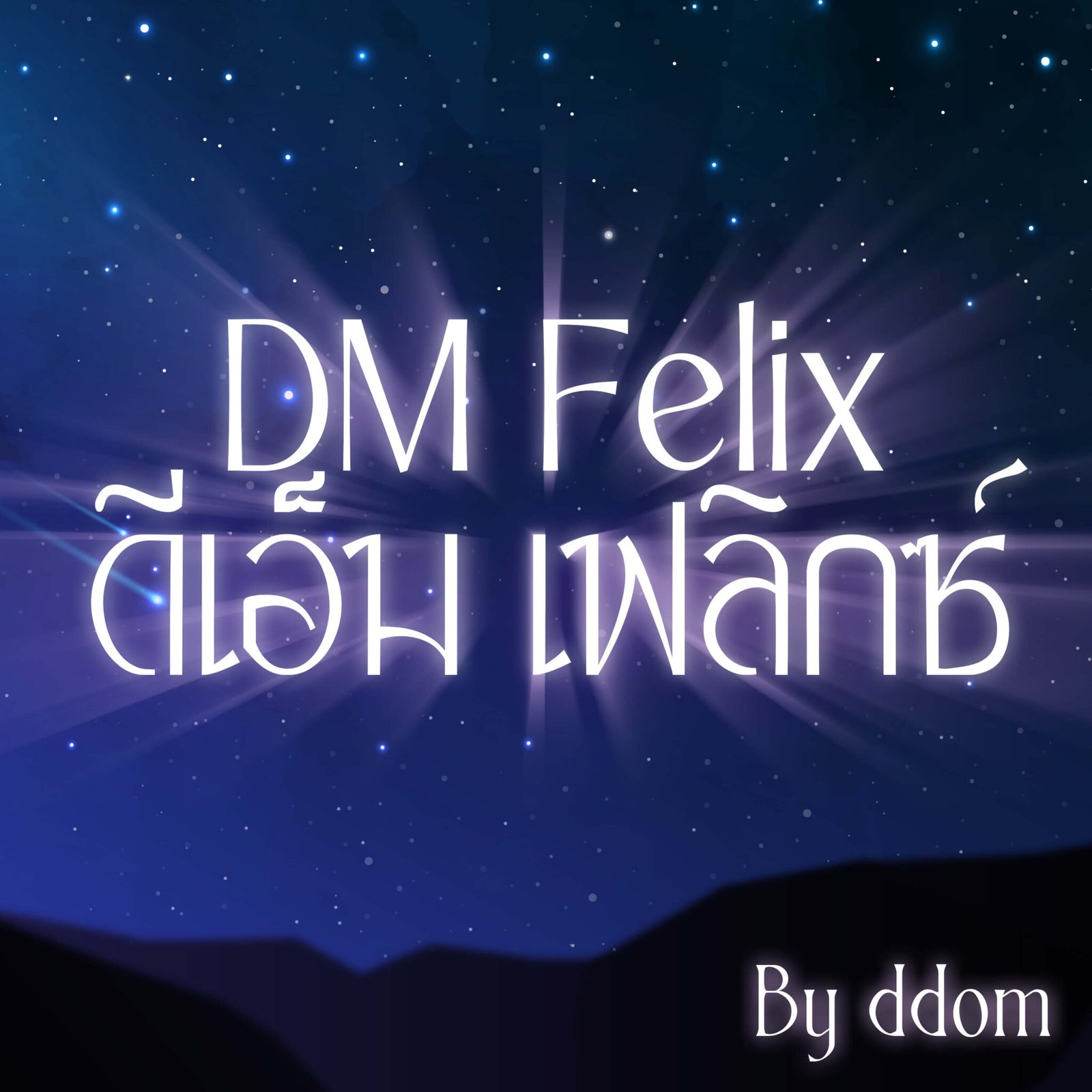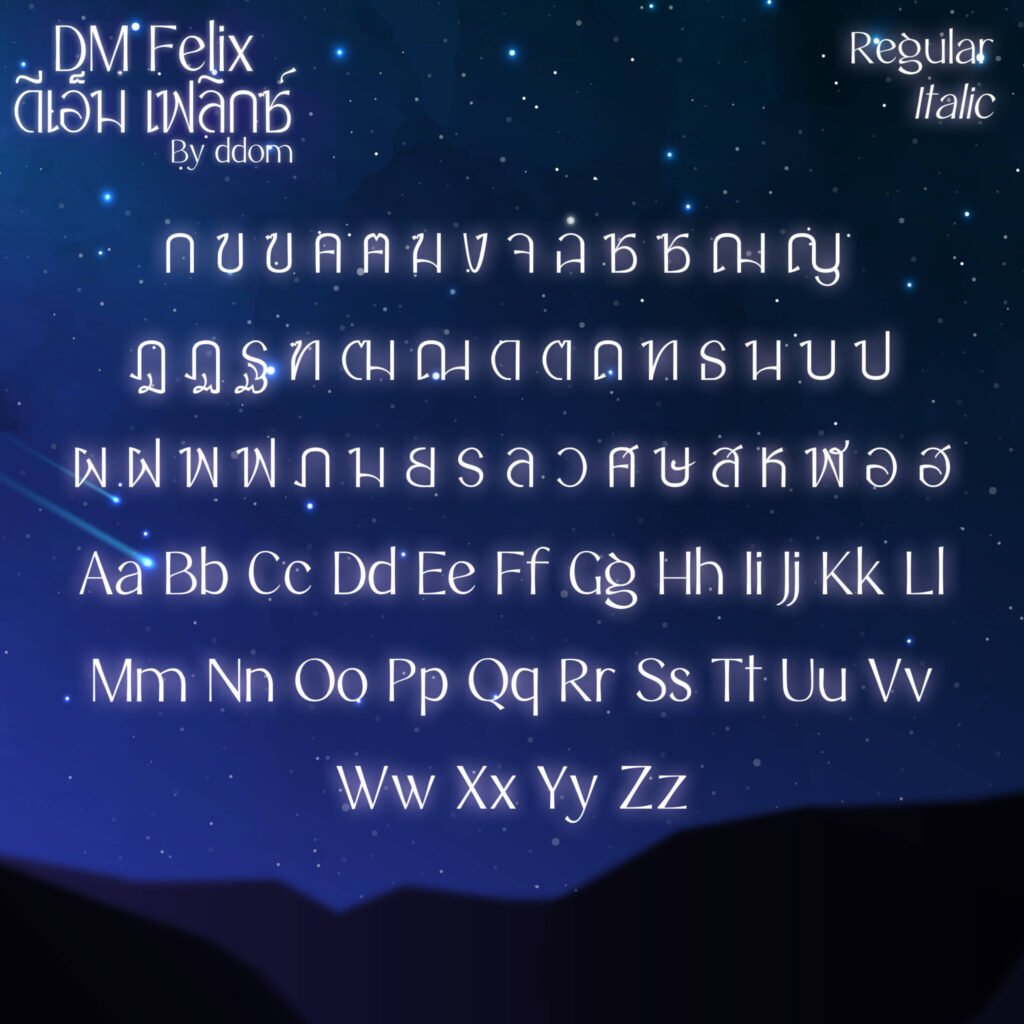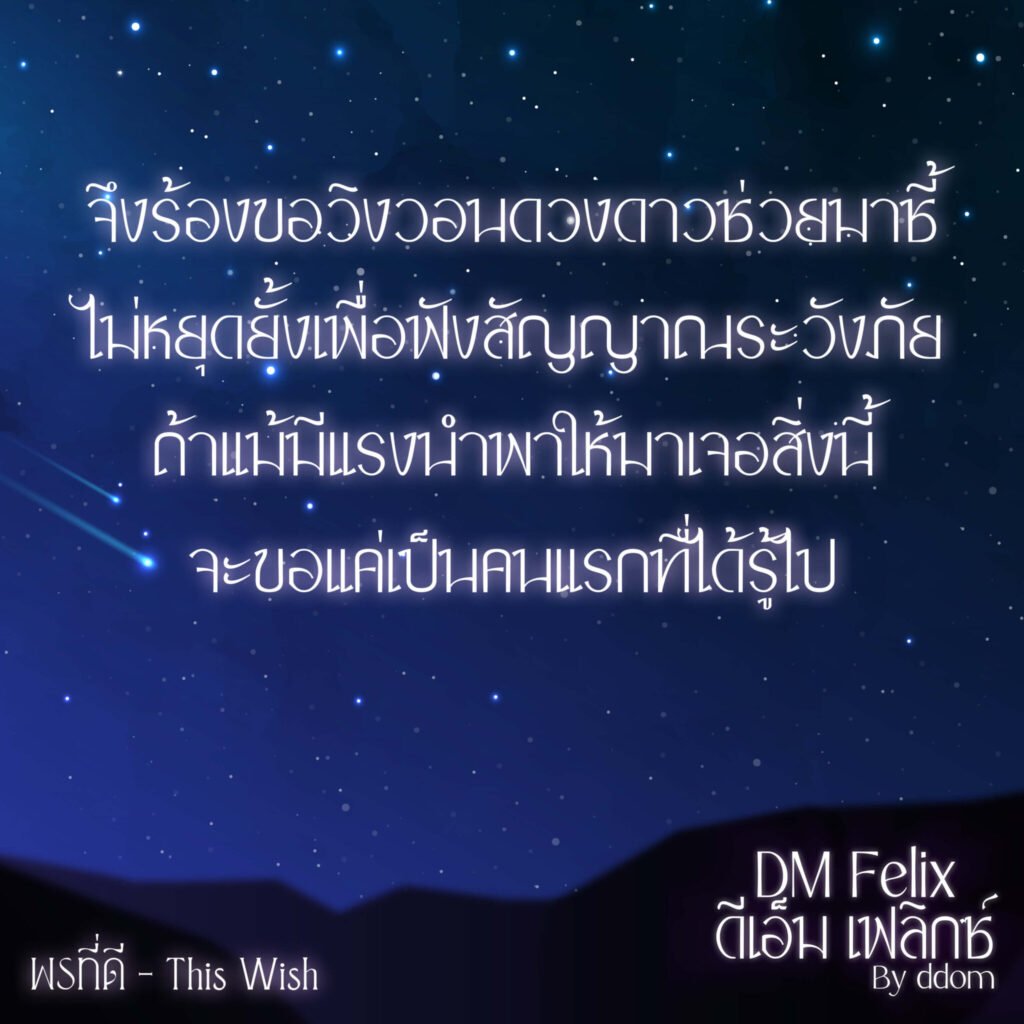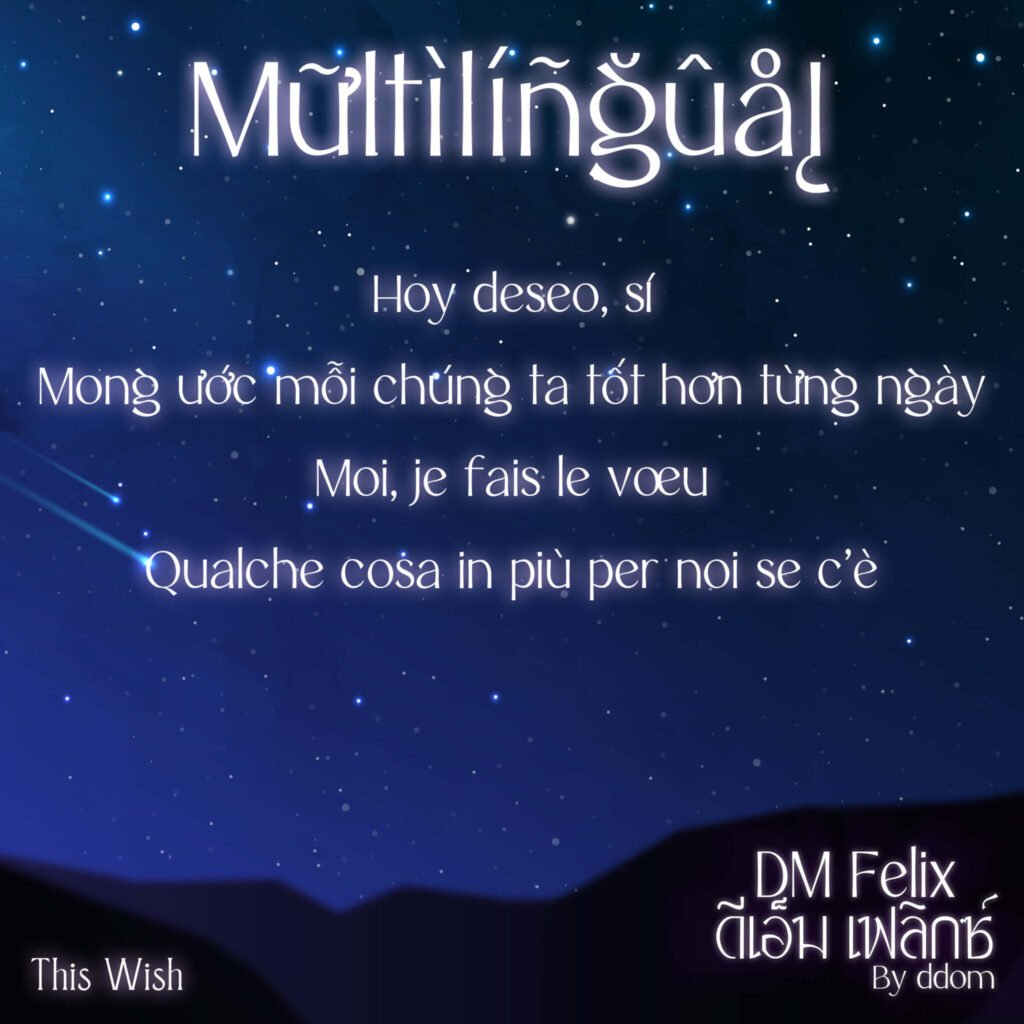
DM Felix (ดีเอ็ม เฟลิกซ์)
ฟอนต์ DM Felix (ดีเอ็ม เฟลิกซ์) ได้รับแรงบันดาลใจในการออกแบบจากภาพยนตร์เรื่อง Wish เหมาะกับการนำไปทำเป็นพาดหัวหรือข้อความสั้นๆ ในโปสเตอร์ต่างๆ